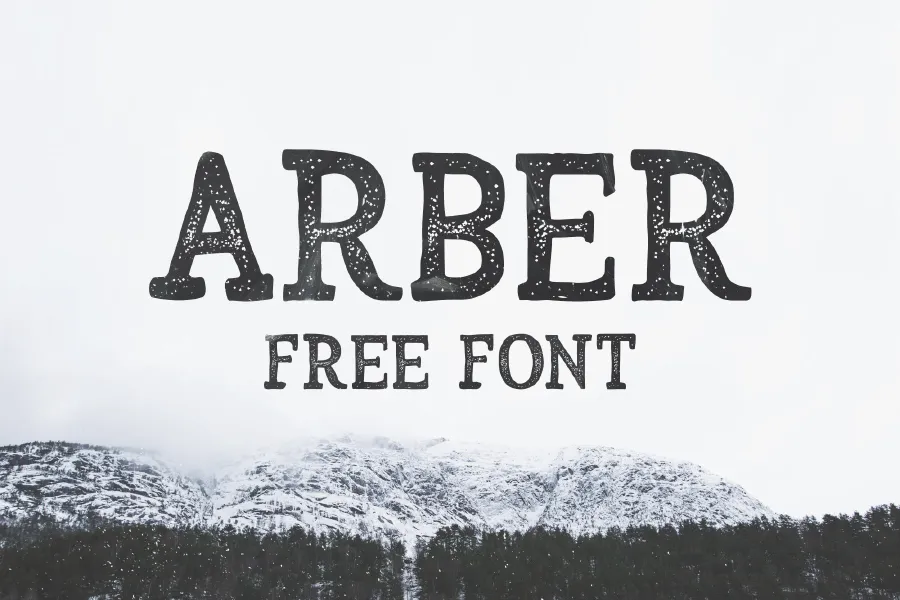
Arber Vintage Font – Download Grátis
Introduzimos Arber! Esta fonte foi criada pelo designer Krisjanis Mezulis. A sua forma é inspirada na técnica de desenho com uma poço fina, feita sobre papel acrílico. Cada letra foi desenhada a mão, dando-lhe um toque artesanal único. Após isso, as letras foram convertidas em formato para fonte e juntas novamente. Este tipo de fonte é perfeito para headlines grandes, logotipos ou cartazes. Arber Vintage Font é um exemplo do poder da arte manual em tecnologia moderna. Inspirada na arte livre dos anos 80 e 90, a arquitectura delicada das letras faz deste um recurso visual inovador que combina a essência de antiguidade com a conveniência de uma fonte digital. Ideal para designers de identidade visual ou qualquer criativo que busque incorporar um toque único em seus projetos visuais.